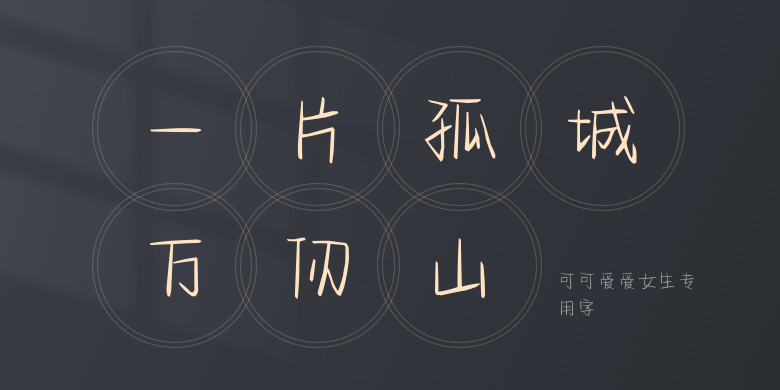
可可爱爱女生专用字
可可爱爱女生专用字,这款字体结构工整、笔画清晰,兼顾美观与易读性,适用于标题、正文、海报、包装、LOGO 等多种场景。字形优雅稳定,风格百搭耐看,适配日常排版与创意设计,让文字呈现更舒适、更具质感。可可爱爱女生专用字一笔一画,皆是细节,以均衡的比例、流畅的线条打造舒适视觉体验,字形端正大气,风格简约现代。无论是商业设计、品牌宣传还是日常排版,都能轻松驾驭,让文字更有格调与力量。可可爱爱女生专用字字体下载。